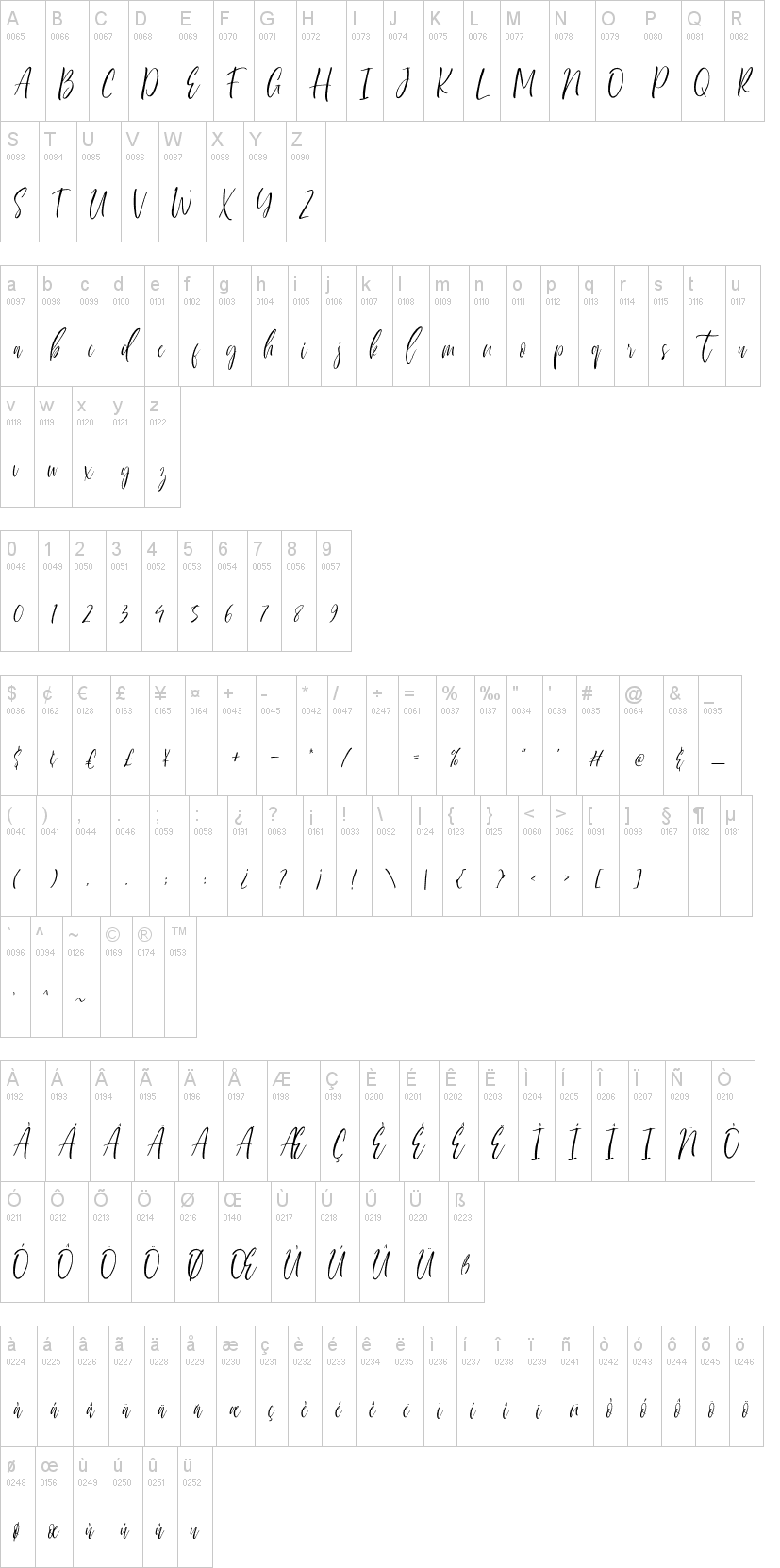
Sherland Modern
Sherland Modern 是一款由英国设计师 Richard Miller 创作的现代风格字体。它具有精致的曲线和清晰的细节,能够提供极具表现力的视觉效果。Sherland Modern 字体具有良好的可读性,可以完美地表达出您的设计理念,并且能够突出文本的内容,更加有助于文本的阅读体验。它也可以用于许多印刷和网页设计项目中,为您的项目增添活力和美感。
Sherland Modern是一款非常不错的手写艺术字体,具有很好的视觉感,适合于文化类的宣传设计、商业类品牌的广告和产品包装设计以及个性化文字排版等较多场景。
Sherland Modern字符映射图